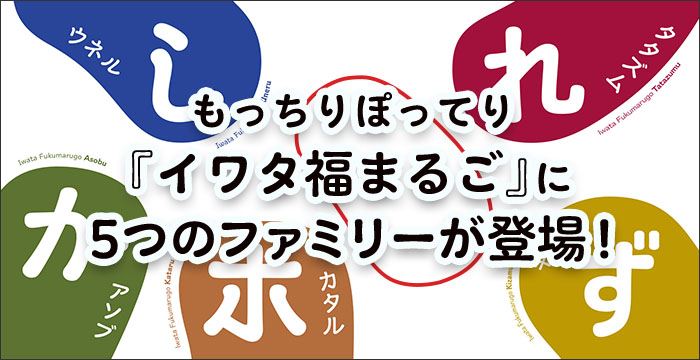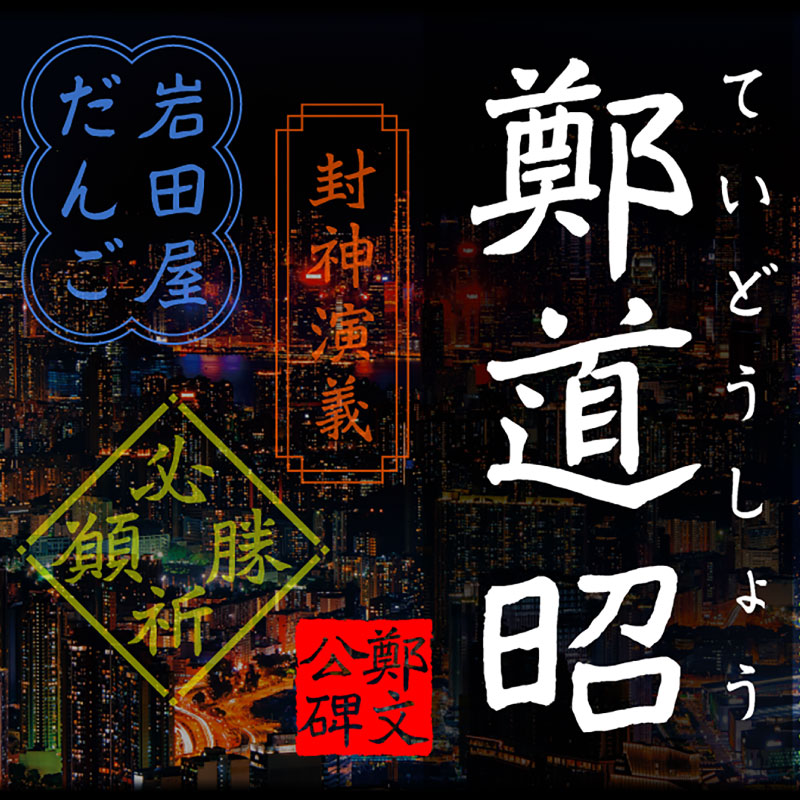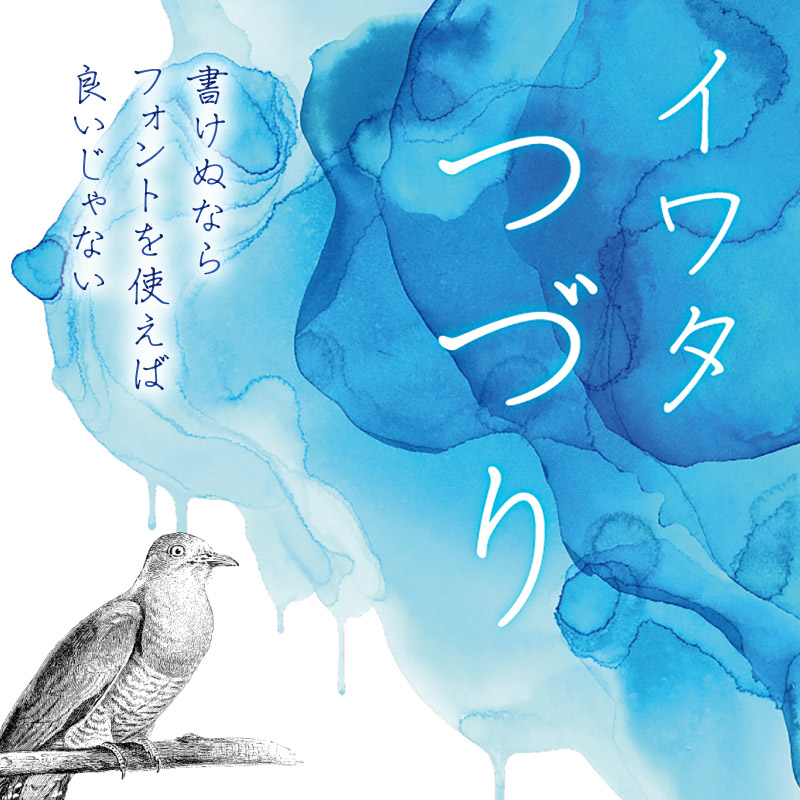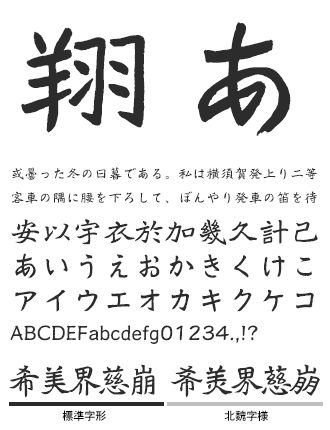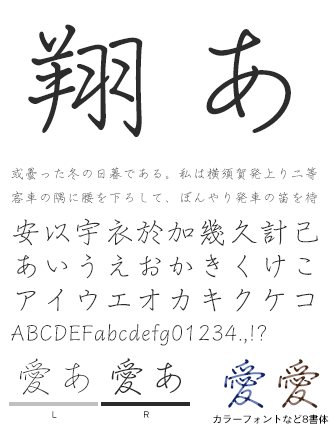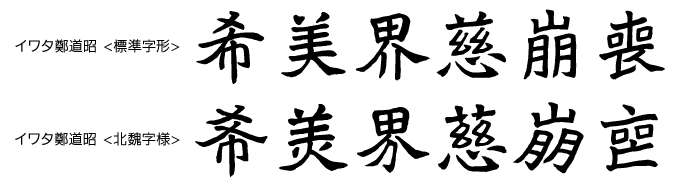
イワタ書体ライブラリー 定番の本文書体から人気書体、最新作まで
活字時代からの伝統と文字作成技術、新しいデジタル化技術が融合した品位の高い書体を多く世に出しているイワタ書体。
金属活字の製造販売から始まったイワタの「文字」への取り組みは、写真植字の時代を経て、最新のデジタルアウトラインフォントの時代の今も、イワタの「文字」への姿勢は創業当時から一貫して変わっておりません。
保有している約30万字のアナログ原字を高品位のデジタルフォントに変換し、多くの印刷業界、新聞社、出版社に採用されています。ラインナップは、明朝体系、ゴシック体系、UDフォント系、教科書体/筆書体系、その他(ミンゴ、アンチック体、ポップ体 など)の全150書体以上と豊富です。
イワタつづり L/R
達筆な人がさらりと万年筆で書いたような、繊細で美しい万年筆風フォント。
Complete Packには、万年筆のインクの濃淡を表現したカラーフォント3種、さらに、お好みのインク色をレイヤーで表現する加工用フォントも収録。
イワタ鄭道昭/イワタ鄭道昭北魏字様
イワタ鄭道昭ていどうしょう / イワタ鄭道昭北魏字様ほくぎじよう
1500年前、中国雲峰山の岩壁に刻まれた鄭道昭の書が現代に蘇る。摩崖碑の風化や岩肌のニュアンスを封じ込めた書体。
現代の標準的な字形に近い「イワタ鄭道昭」と、拓本に倣った「イワタ鄭道昭北魏字様」の2書体セットです。
イワタ福まるご L/R/M/B/E
有機的な曲線で構成された、これまでにないシルエットの丸ゴシック体。「もっちりぽってり」。見出しから、しっかり文字組までこなせます。
イワタ福まるごアソブ L/R/M/B/E
カジュアルさの中に軽快なリズムを持たせた書体で、親しみやすい遊び心に、ノスタルジックな面持ちも備えています。その姿は原っぱで楽しく遊んだ少年時代を連想させます。
イワタ福まるごウネル L/R/M/B/E
右上がりで華やかな書体です。装飾的な曲線を多く用いた芸術「アール・ヌーヴォー」から着想を得たデザインで、その様式は浮世絵からも影響を受けていると言われます。うねるような筆遣いは北斎の大波を想起させます。
イワタ福まるごカタル L/R/M/B/E
映画字幕などで使われていた特徴的な文字をモチーフにした書体です。線画が長く高低差の少ない骨格と、線端の抑揚が手書きのイメージを伝えます。レトロな映写機で映し出された名作が優しくゆっくりと語りかけるかのようです。
イワタ福まるごタタズム L/R/M/B/E
金属活字の古いゴシック体の骨格と幅広な欧文を合わせた書体です。味のあるアンバランスさや小さな拗促音など活字時代に培われたテイストを色濃く取り入れています。時代を超えても色あせない重厚な佇まいは、夕日に染まった富士山を彷彿とさせます。
イワタ福まるごキザム L/R/M/B/E
(横書き専用書体)
イワタ福まるごキザム L/R/M/B/E
水平垂直に構成された長体かなを、横方向のラインに沿って揃えた機械彫刻のような横書き専用書体です。タイプライターで規則正しく打たれたような律儀さに柔らかい曲線が合わさり、整然としていながら堅苦しくない印象を刻みます。
イワタ明朝体オールド R/M/D/B/H
起筆、終筆部のアクセントで表現された活字特有の文字の力強さ、小さめにデザインされたかなは可読性を高めます。
イワタUDシリーズ UD明朝・UDゴシック・UD丸ゴシック・UD新聞書体
イワタUD書体シリーズ R/M/D/B/H
ユニバーサルデザイン(UD)の視点で開発されたシリーズです。UD明朝、UDゴシック、UD丸ゴシック、UD新聞明朝、UD新聞ゴシックと充実のラインナップ。
イワタミンゴ M/D/B/E/H
明朝体のシャープさ・可読性の良さと、ゴシック体の強さ・整斉さを兼ね備えた、スッキリと読みやすいデザインの格調ある書体です。
イワタアンチック体 M/B/E
アンチックのかなとゴシックの漢字を1フォントに統合。マンガの吹き出しや辞書の見出しによく使用されます。80年以上の歴史がある「イワタアンチック体」の復刻版です。
イワタ宋朝体 M/D/B
シャープな角線と点画の鋭い端が特徴の格調高い伝統書体。正方に近い岩田母型の方宋体活字をもとにデジタル化。
活字時代の漢字・仮名を再現した「イワタ宋朝体」と、仮名のデザインを現代風にアレンジした「イワタ宋朝体 新がな」があります。
5修正・出力
アウトラインデータを1文字1文字、モニターや紙で確認・修正をします。
6監修・修正作業
出力された文字をデザイナーが、1文字1文字綿密に修正指示を行います。その指示に従い、オペレーターが修正作業を行います。これはデザイナーが納得するまで、何度も繰り返します。高度なテクニックと人並み外れた忍耐力の勝負です。
7エレメント作成
出来上がった数百文字をもとに、エレメント(部品)を作成します。このエレメントを元に、オペレーターが OTF Pro であれば1万5千字ほどの文字を作成します。
8監修・修正
作成された文字を文字組し、文字のつぶれや並びなどのデザインの不具合を修正します。その修正が終わると、ようやく文字デザインが終了します。
9フォント化
完成した文字もそのままでは販売はできません。ソフトウェア技術者がプロポーショナルデータ (文字ごとに最適な幅を設定) などを付け加え、OSやアプリケーションとの組み合わせを検証します。検証項目は数百に上ります。こうしてようやく、1書体 (フォント) が完成します。